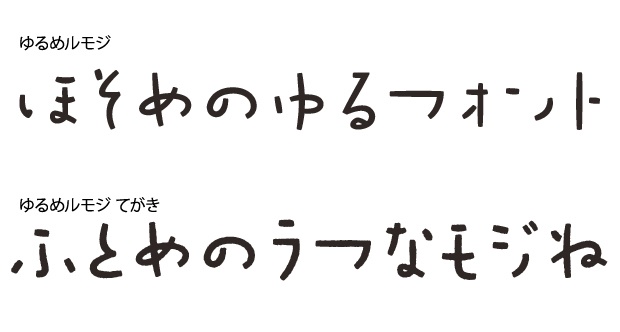
ゆるめルモジ フォント
ゆるいセリフ、フワッとした会話など脱力感のあるシーンをイメージしたフォントです。使うだけで、雰囲気をゆるめる効果がある脱力系フォントです。女の子の手書きフォントのような可愛さがありつつも、どこか書家の文字のような伝統的な要素もあればと思い制作しました。 漫画のシーンに添えるちょっとした文字にも、デザイン要素として少しゆるい雰囲気が欲しいときにも活躍すると思います。やや太めで手書き感のあるラフな「ゆるめルモジてがき」も収録されています。こちらの方がロゴに向いていると思います。
ひらがな、カタカナのみの書体になります。